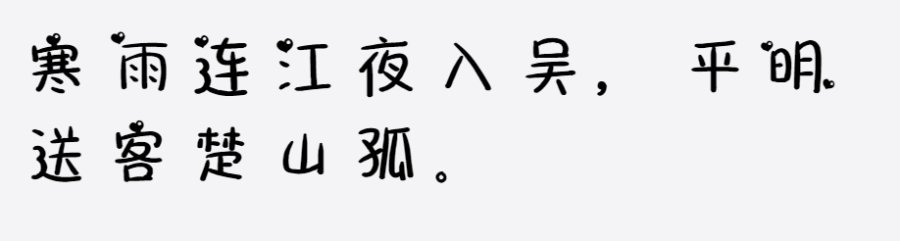
适合情人节海报字体有哪些?
又到浪漫情人节了,设计师也到了挺忙的时候了,各种加班设计浪漫作品,特别是情人节的海报,设计海报字体的选择也是非常重要的,总不能使用大黑体吧,这时候我们就应该选择一些可爱型,浪漫型的字体。如X-刚好遇见你,光是看名字就是知道满满恋爱的心意了。
X-刚好遇见你
遇见你心河长明